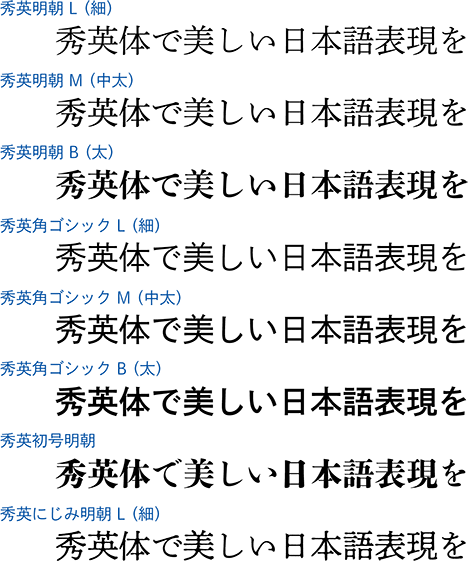
『秀英体』の8フォントを「一太郎2019」にライセンス提供
大日本印刷株式会社(DNP)は、DNPのオリジナル書体『秀英体』の8フォントを、日本語ワープロソフトなどを開発・販売する株式会社ジャストシステムにライセンス提供します。
秀英体の魅力を凝縮したフラッグシップ「秀英初号明朝」に、ご好評いただいているにじみシリーズ第一弾の「秀英にじみ明朝」を含む、豪華なラインナップが揃います。さまざまなシーンで是非、ご利用ください!